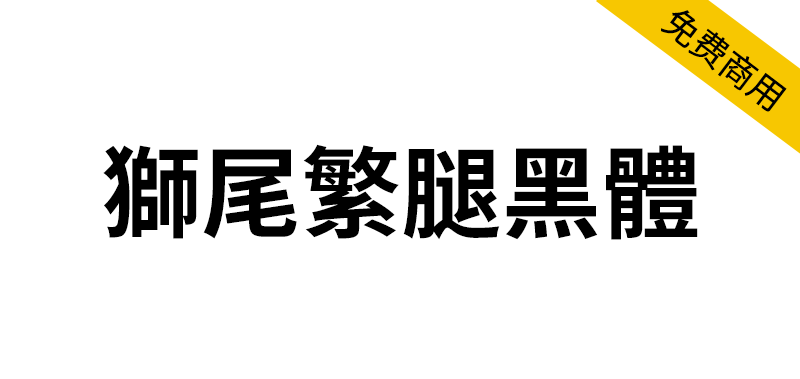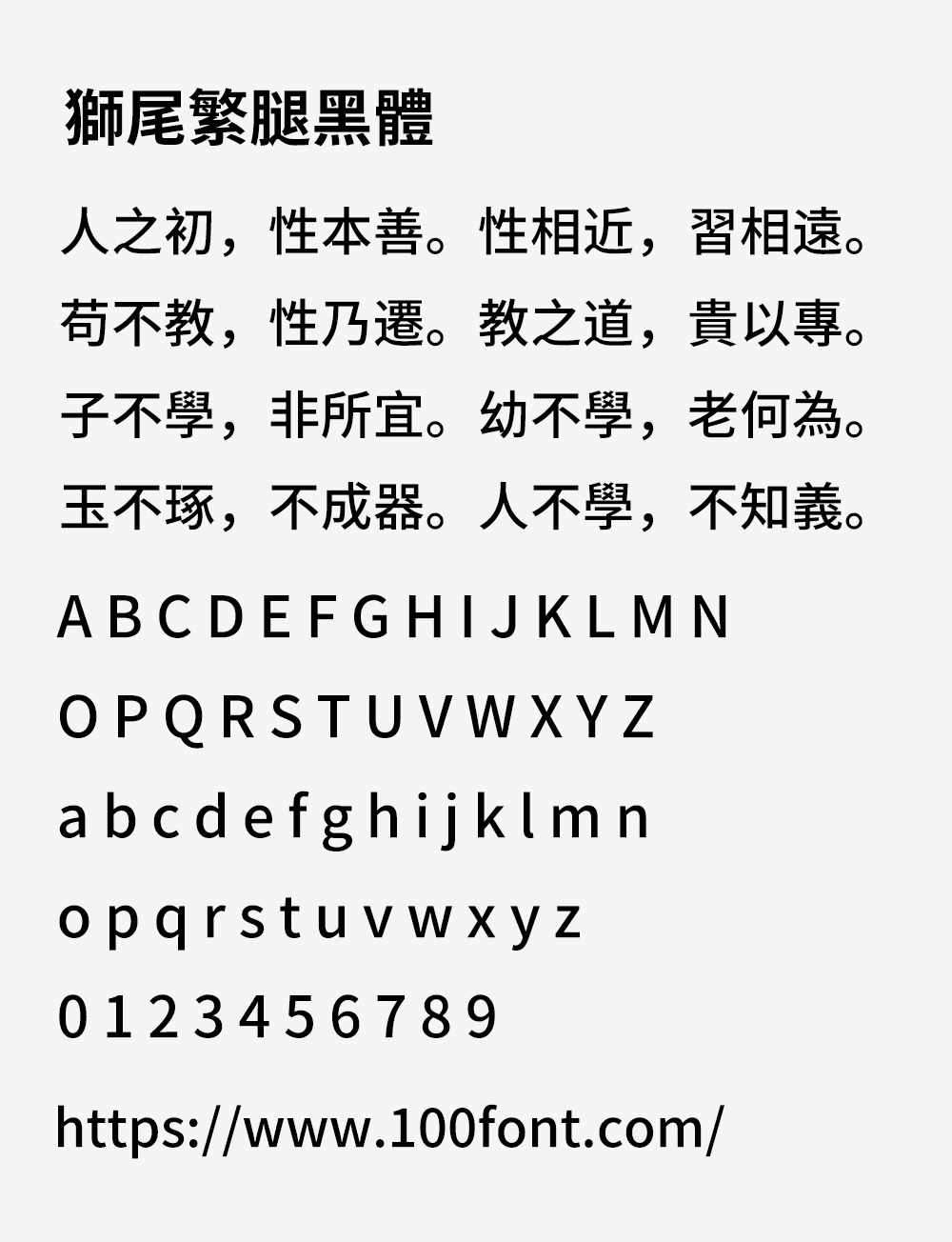
狮尾繁腿黑体基于思源黑体的简转繁字型(简转繁的意思就是输入简体字时,会自动显示成繁体字),狮尾繁腿黑体的特色是「简体字转成繁体字的字型档」,没有很完美,比完全没转换好一点,不能处理「一简对多繁」。狮尾繁腿黑体设计上针对笔画粗细有7种字重,所以不论大标、小标、简单的段落排版都能清晰辨识。可以免费商用,欢迎大家自由应用、自由优化、自由改作!
狮尾繁腿黑体与「狮尾繁中黑体」与差别在有没有拔脚,「拔脚」就是会有较少的笔画,例如移除「口」字的左右下角会多出的短线条。有拔脚的字会较圆,但是会造成有些字因直接去掉腿后左右不平衡、左右不对衬的「悬空」问题。改使用「腿」系列字体就不会有这个问题。